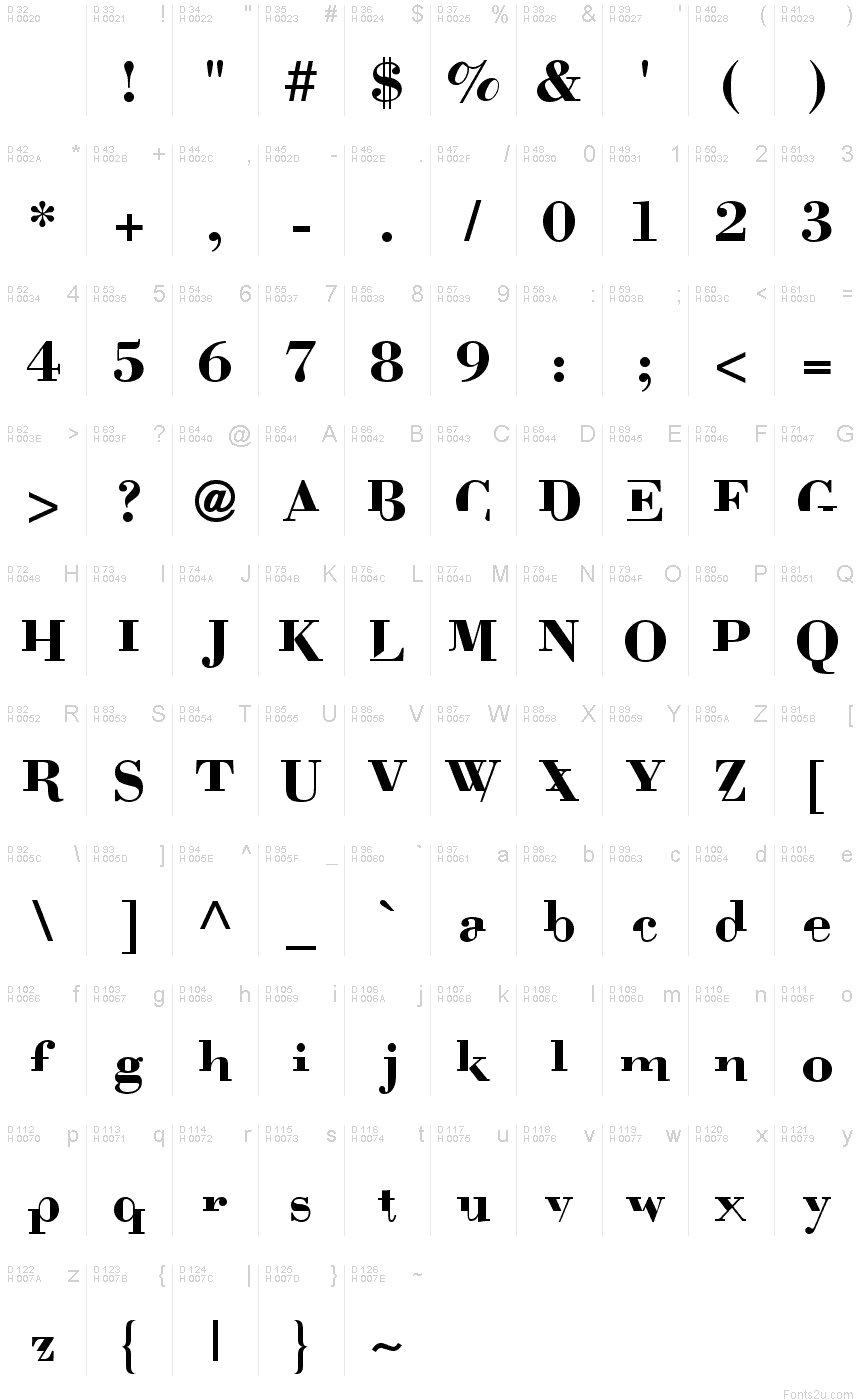
BodoniMutant
Bodoni Mutant to bezpłatny dekoracyjny krój pisma typu display, który przekształca klasyczną elegancję Bodoni w coś bardziej dziwnego i teatralnego. Solidne pionowe linie zderzają się z nierównymi krzywymi i nieoczekiwanie zwężającymi się łączeniami, nadając każdemu słowu lekko ekscentryczny, eksperymentalny klimat. W dużych rozmiarach tuszowe, blokowe litery wydają się niemal rzeźbione, jakby wycięto je w czarnym lakierze, zamiast po prostu narysować na ekranie.
Bodoni Mutant to odważny głos dla projektów, które wymagają charakteru i dramatyzmu: plakatów artystycznych, sesji modowych, okładek książek, identyfikacji wizualnych galerii, okładek albumów i niebanalnych logotypów. Światło między literami sprzyja tworzeniu ciasnych, wyrazistych znaków słownych, które odbiera się równie mocno jako formy graficzne, co tekst. Ten bezpłatny font świetnie komponuje się w mniejszych rozmiarach z prostym, geometrycznym bezszeryfowym krojem, pozwalając Bodoni Mutant przejąć nagłówki, podczas gdy tekst uzupełniający pozostaje czysty i stonowany.